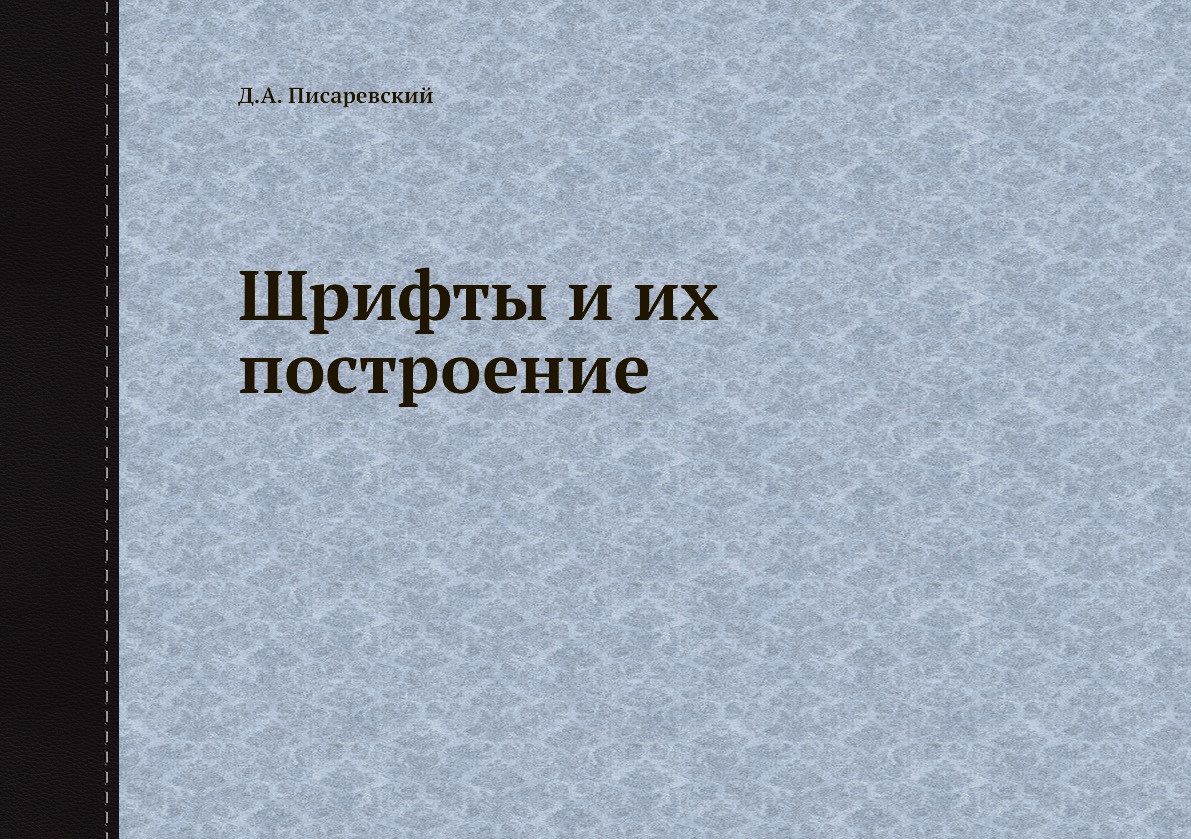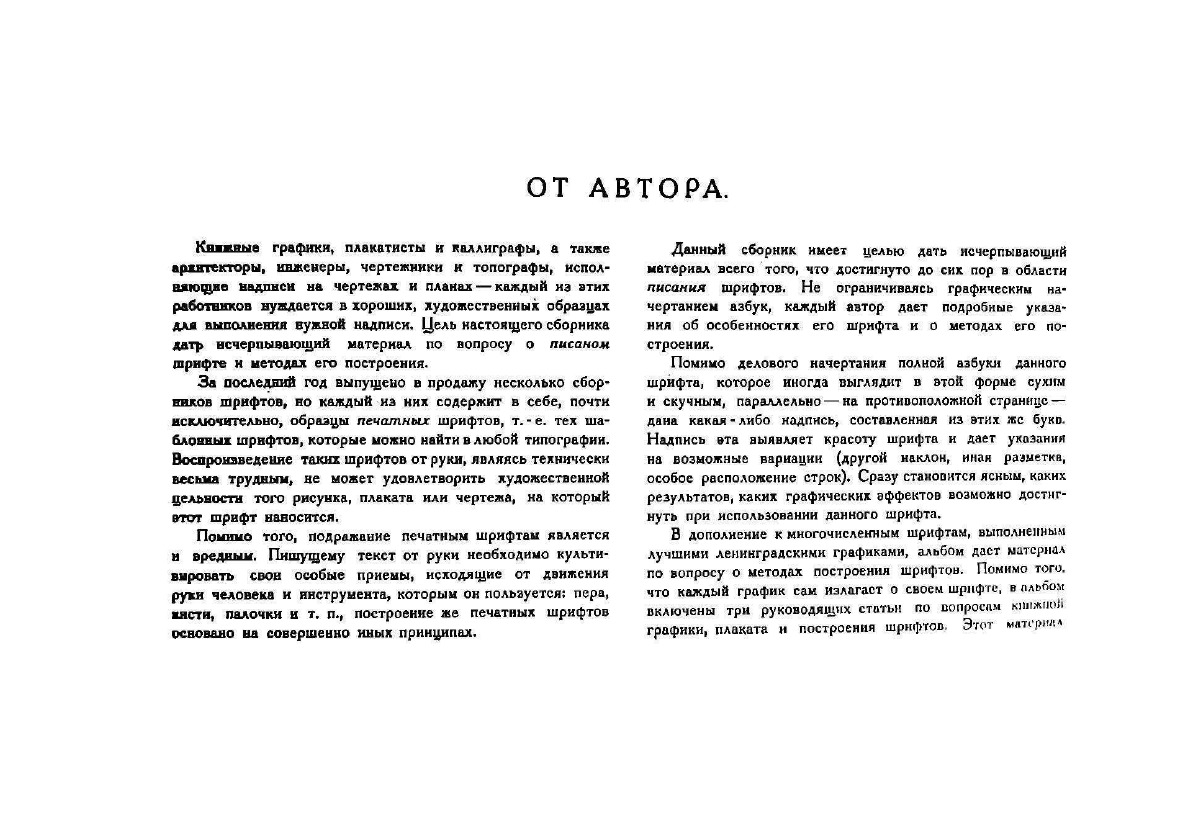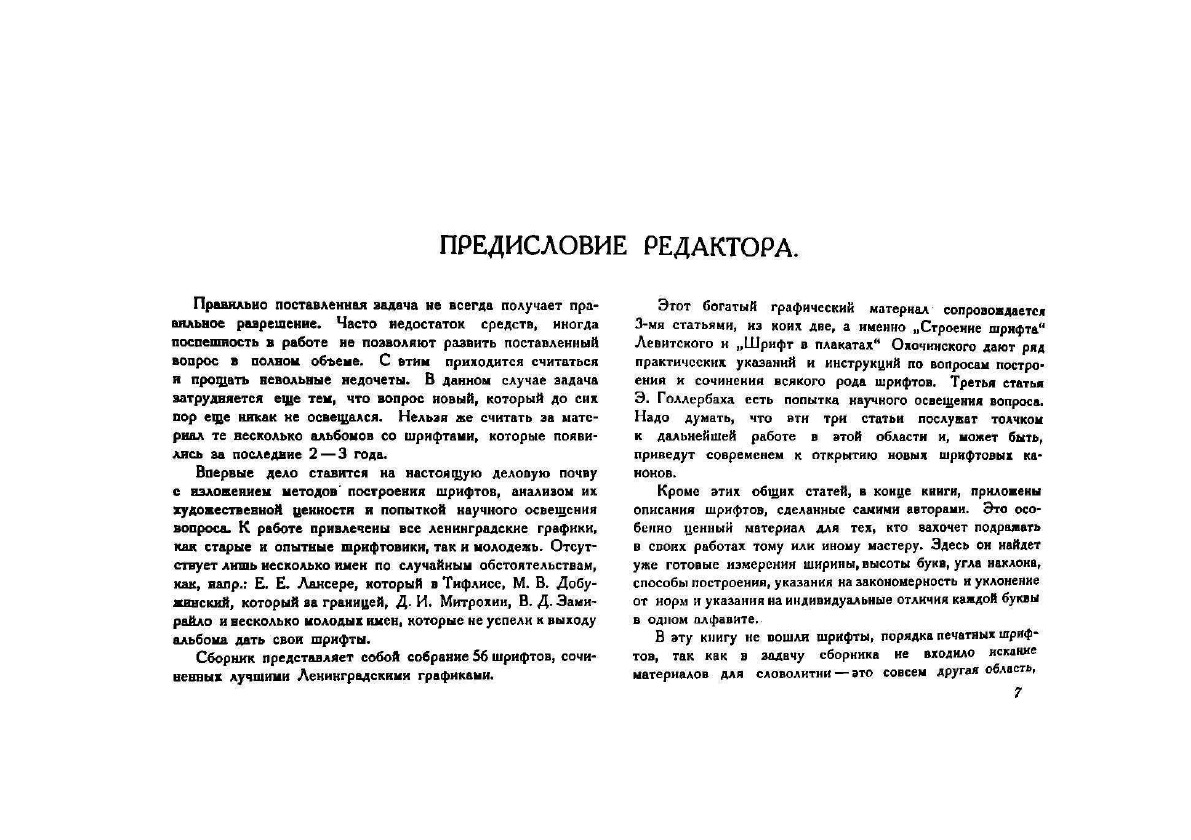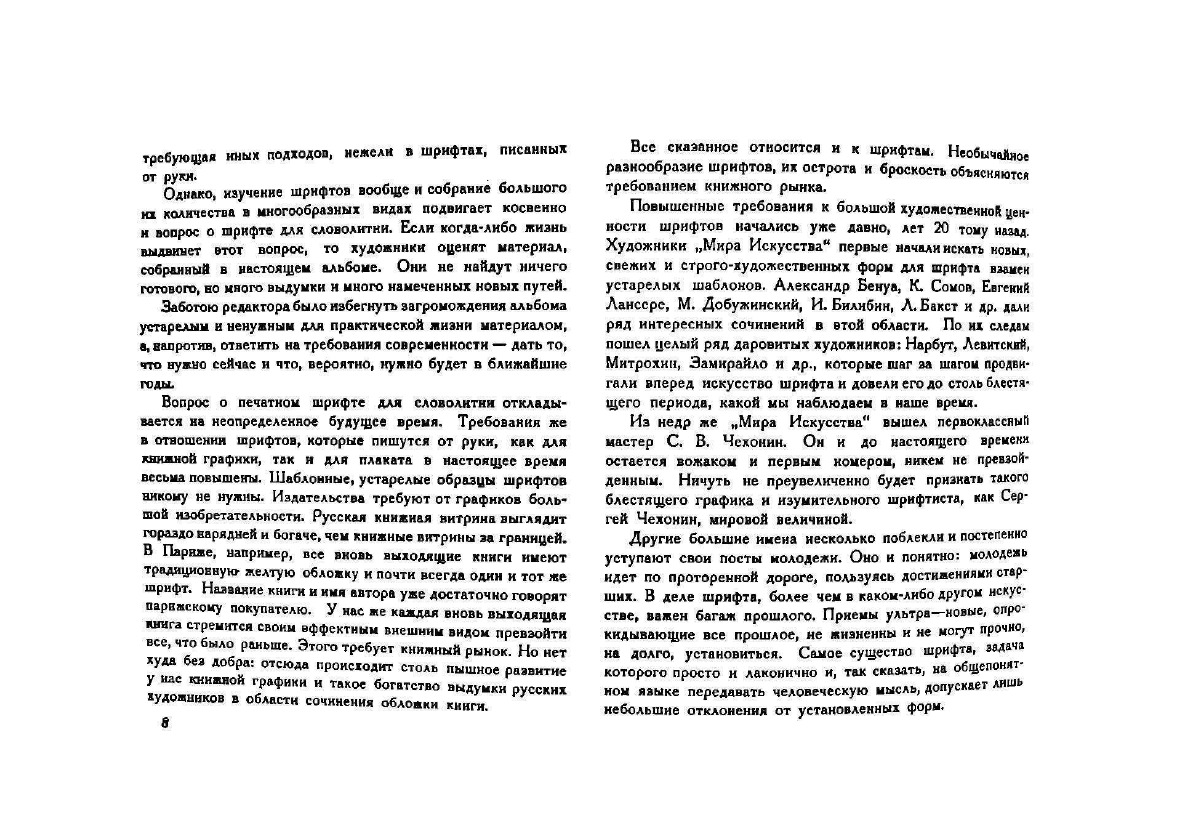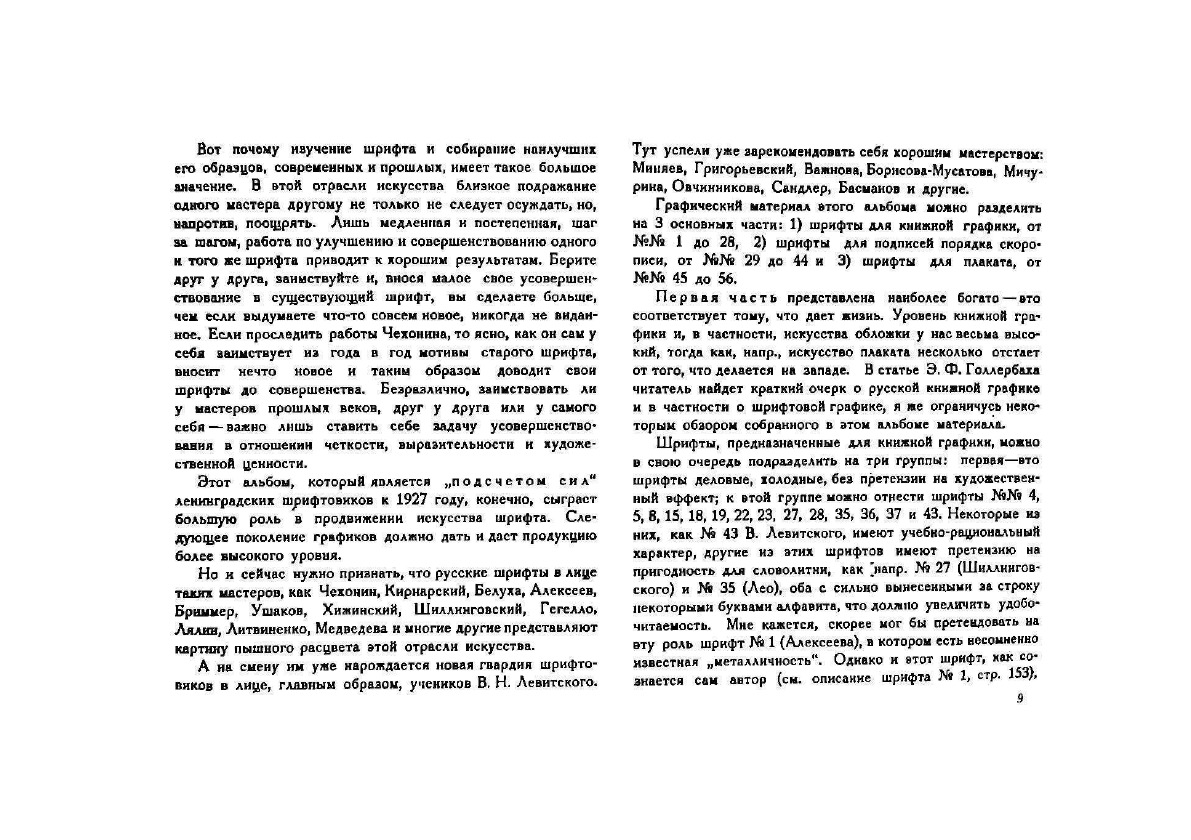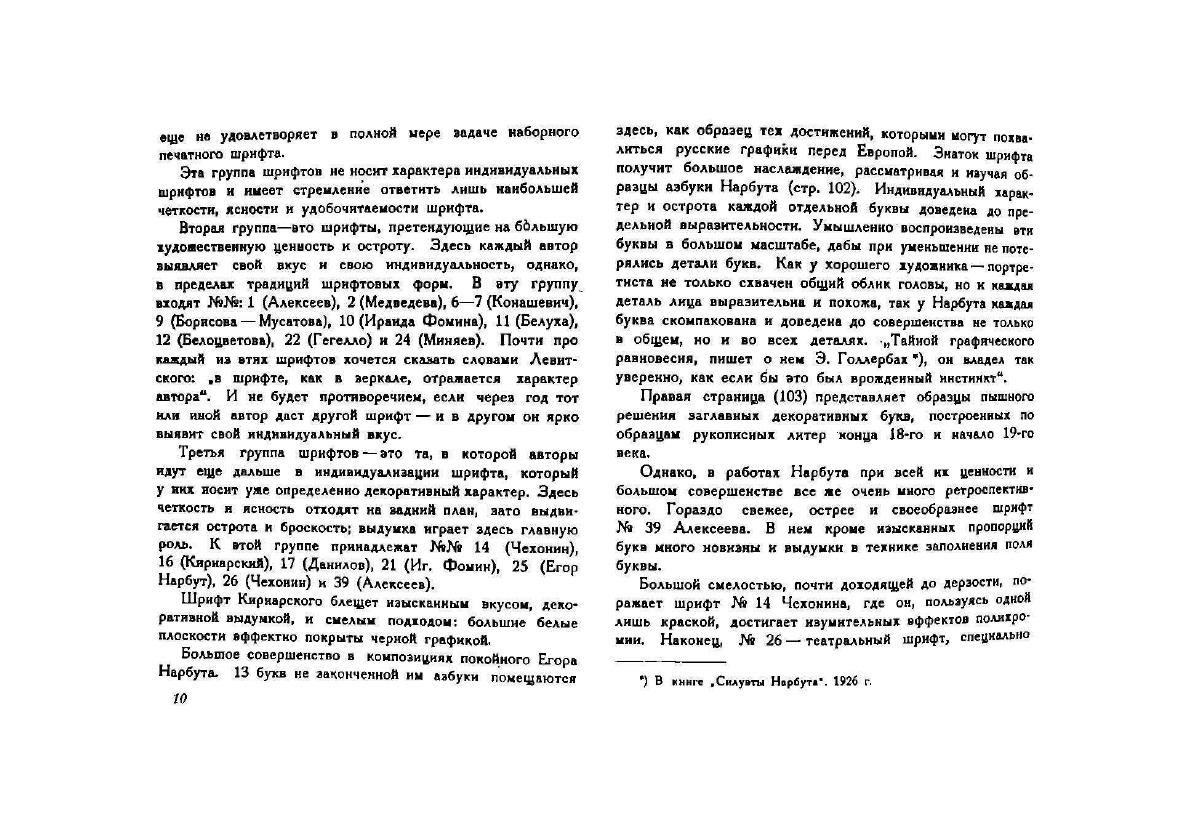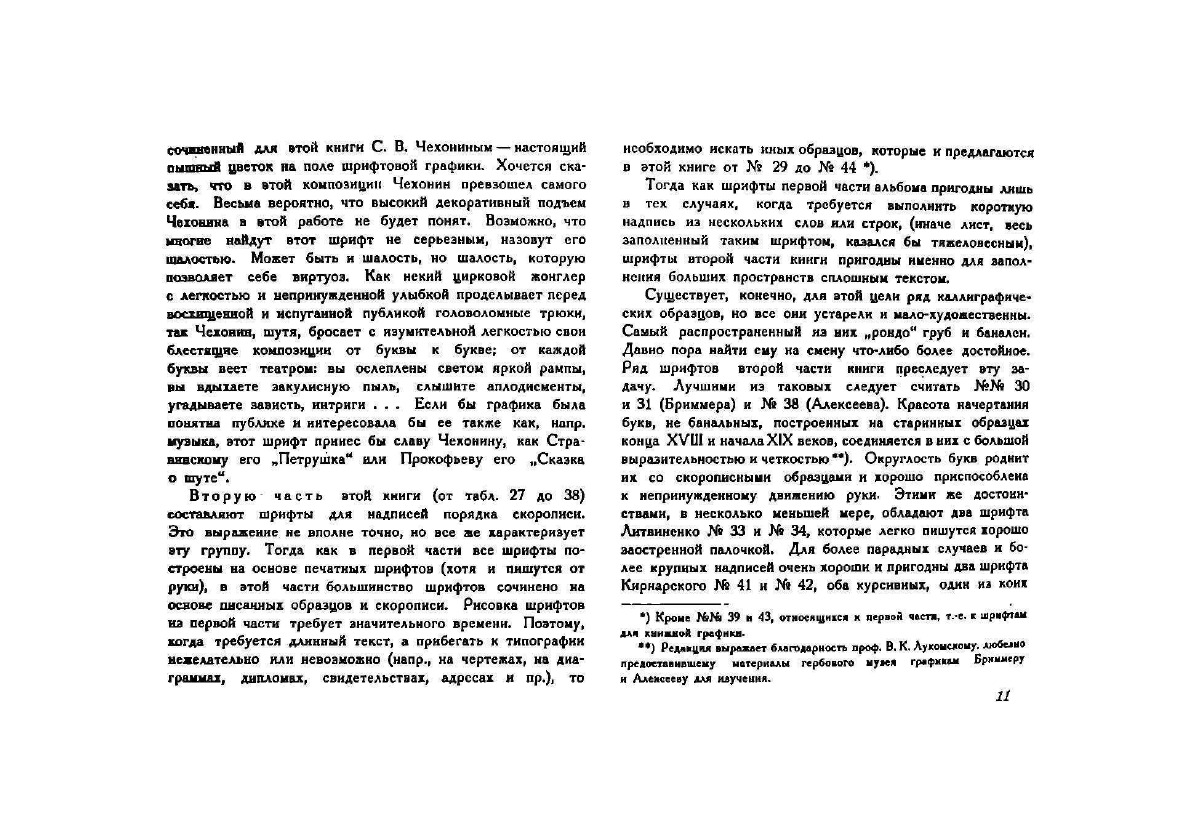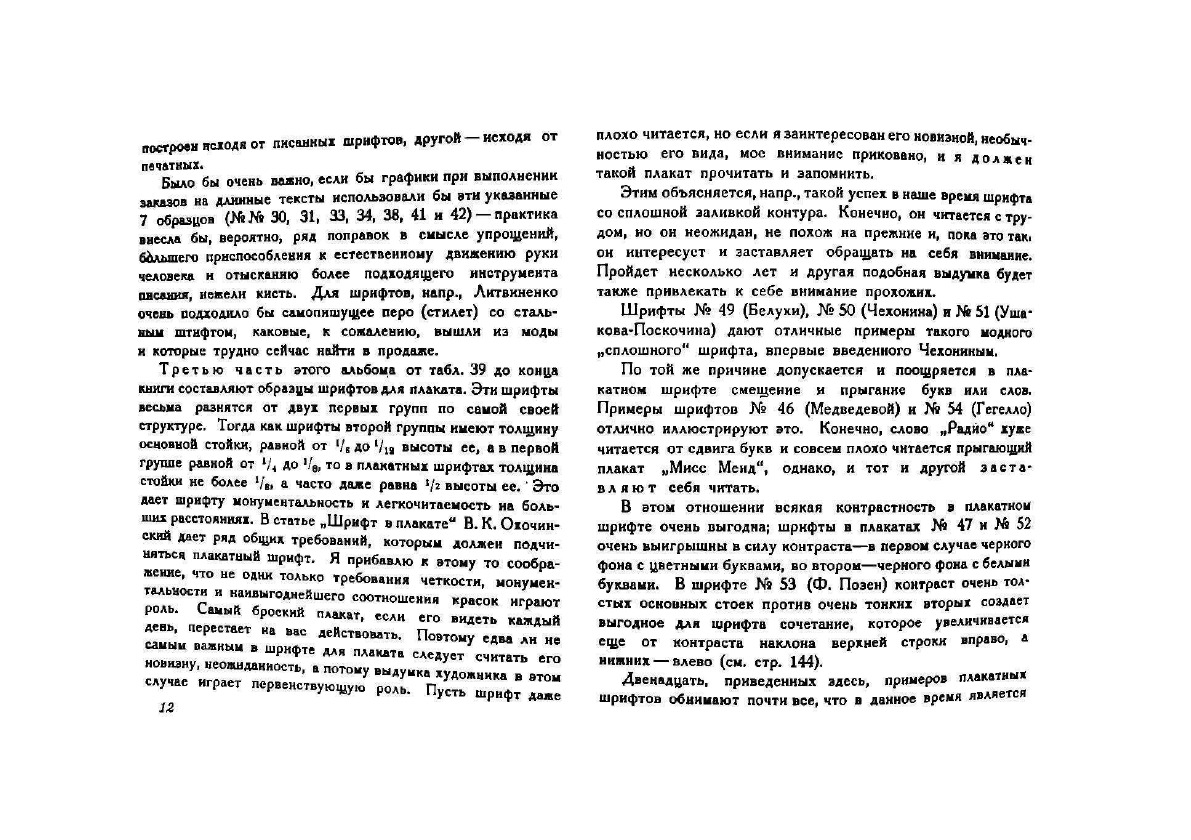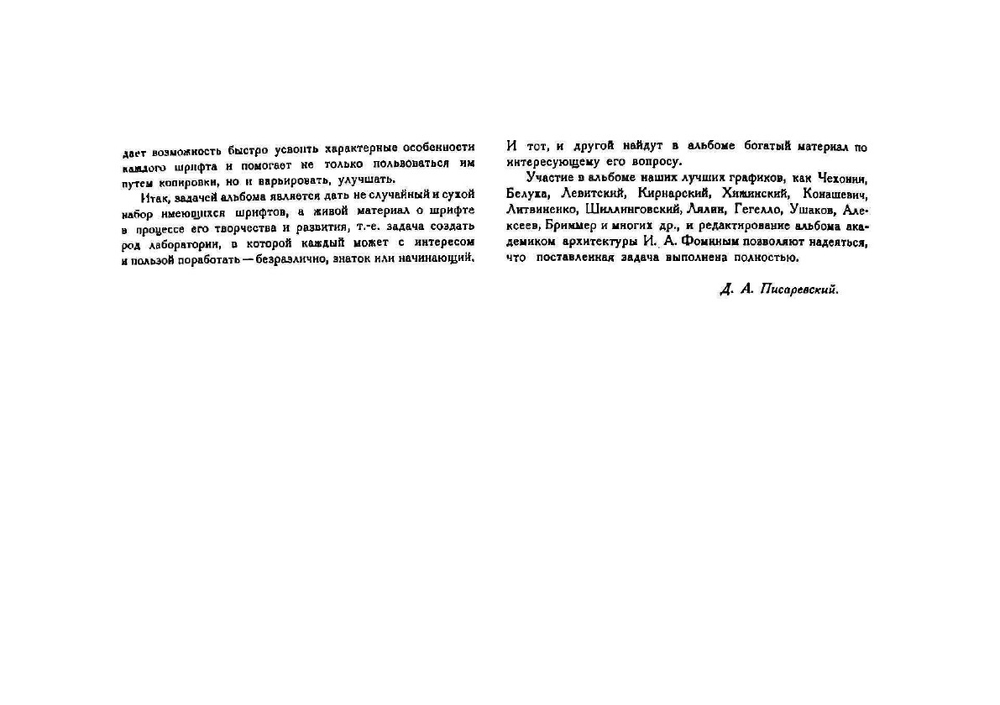
Альбом представляет достижения ленинградских графиков в области декоративного рукописного шрифта (56 шрифтов). Вклюкает три статьи: Левитский В. Н. «Строение шрифта», Голлербах Э. Ф. «Применение шрифта в книжной графике», Охочинский В. К. «Шрифт в плакате».